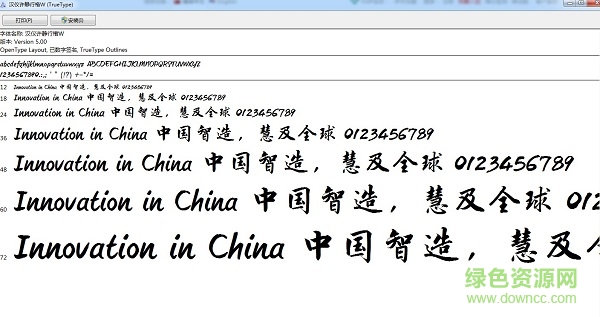
汉仪许静行楷字体
汉仪许静行楷w字体是一款蕴含古典气息的行楷字体,线条流畅,结构端正,字形优美,影视海报、招牌设计、古籍封面等均可使用该字体,有需要者欢迎免费下载!
行楷字体特点
汉字的一种书体,是行书与楷书的结合,一般的理解是字中楷多行少,是借鉴行书笔法的楷书,其最大特点是在楷书结构的基础上融入行书的连带笔法。变端庄严肃为活泼跳动,但基本不作过多的简省,大致保持楷书风貌。
汉仪许静行楷w